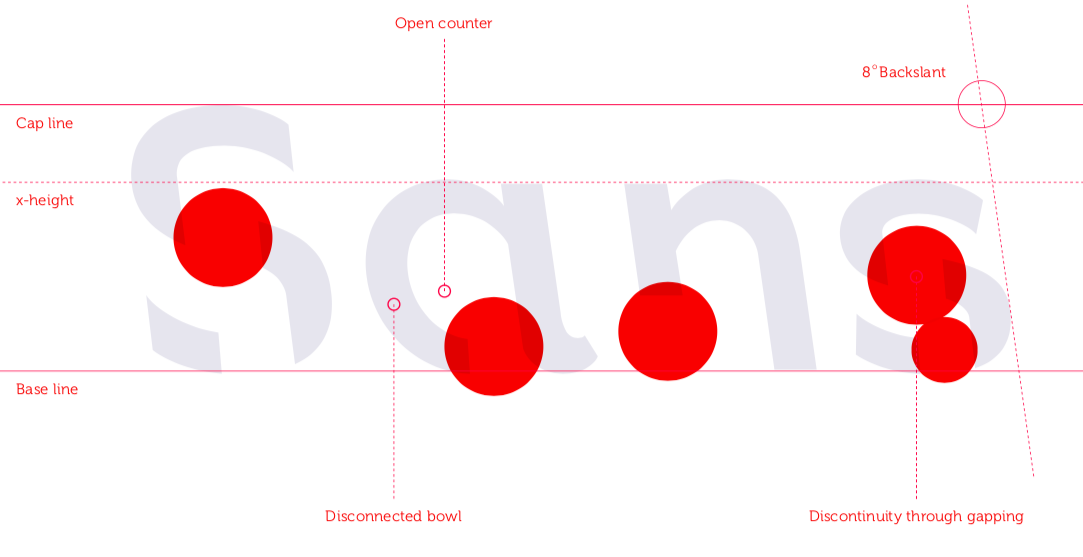
Il font fatto per essere ricordato
Il Sans Forgetica è volutamente difficile da leggere: per far fare più fatica al cervello, e imprimere nella memoria quello che si è letto
A inizio ottobre l’RMIT – una delle più importanti università australiane, con sede a Melbourne – ha presentato un nuovo font, progettato per rendere le cose scritte più facili da ricordare. Il font si chiama Sans Forgetica ed è basato sul principio della difficoltà desiderabile, secondo il quale nell’imparare o scoprire qualcosa è meglio incontrare qualche ostacolo non troppo grande, perché la fatica, se non è eccessiva, aiuta a ricordare meglio. Sans Forgetica è quindi volutamente un po’ difficile da leggere, cosa che fa fare al cervello un po’ di fatica in più rispetto al solito e impedisce di leggere meccanicamente. È fatto così:
Sono parole a cui dovreste aver dedicato più attenzione rispetto a quanto avreste fatto altrimenti, leggendole così: Sans Forgetica è gratis e dopo averlo scaricato si può usare sui principali programmi di Mac e PC, o si può installare un’estensione di Google Chrome che permette di evidenziare alcuni estratti di testo e trasformarli in estratti scritti in Sans Forgetica.
Il gruppo di lavoro che ha creato Sans Forgetica per il RMIT (Royal Melbourne Institute of Technology) era formato da grafici ed esperti di caratteri tipografici della School of Design e da psicologi del Behavioural Business Lab. Hanno spiegato di aver voluto creare un font con premesse opposte rispetto a quelli “puliti e lisci” che vanno di moda oggi, soprattutto per testi da leggere su schermo. Il problema, spiegano, è che «se un’informazione viene letta in modo troppo facile e pulito, non riesce a stimolare il cervello per dare il via a quel processo cognitivo più profondo che è indispensabile per immagazzinare e ritrovare».
I ricercatori del RMIT hanno creato un font in cui le cui lettere erano incomplete e avevano un backslant: una leggera pendenza verso sinistra. Le lettere incomplete funzionano come certe immagini che offrono solo dei pezzi e lasciano che sia il cervello a metterci gli altri. Il logo del WWF, per esempio, è fatto di macchie nere: è il cervello a fare il resto e vederci un panda.
Il backslant è invece una pendenza che va in direzione opposta rispetto a quella usata nel corsivo e in tipografia gli unici nomi scritti con una pendenza verso sinistra anziché verso destra sono quelli dei fiumi, sulle cartine.
Dopo aver creato tre versioni diverse del font, i ricercatori hanno chiesto a circa 400 studenti di leggere informazioni scritte in quei tre font e hanno notato che quello che permetteva di ricordare di più era quello intermedio: uno era troppo “normale” e l’altro troppo “incompleto”. Hanno detto che mentre gli studenti ricordavano il 50 per cento di un testo con un font normale, nel caso di Sans Forgetica la percentuale saliva al 57 per cento.
Del lato creativo di Sans Forgetica si è occupato Stephen Banham, un noto tipografo e professore di tipografia, creatore di circa 20 font, che si è però trovato a dover sovvertire molti dei principi base della realizzazione di un font: anziché farne uno facile ha dovuto farne uno difficile, ma non troppo. Banham ha però spiegato che il font «non è fatto per leggerci dei romanzi, perché in quel caso farebbe solo venire dei potenti mal di testa». Janneke Blijlevens, una delle ricercatrici che ha lavorato a Sans Forgetica, ha ricordato che è fatto per studenti, persone che devono ricordare qualcosa: «Serve per evidenziare un passaggio chiave, come una definizione, non per altre cose». Ha anche spiegato che potrebbe tornare utile a chi sta cercando di imparare una lingua straniera.
È difficile trovare recensioni di un font, specie di uno nuovo e particolare come questo. Per ora ne hanno parlato importanti giornali come il Guardian e il Washington Post, ed è difficile fare una stima di come ne parla su internet chi dice di averlo provato: su Reddit c’è una discussione tra chi dice di apprezzarlo, chi dice che è fastidioso e inutile (o comunque meno utile di un evidenziatore) e chi si chiede se l’effetto sulla memoria funzioni a lungo, o solo sui primi estratti.